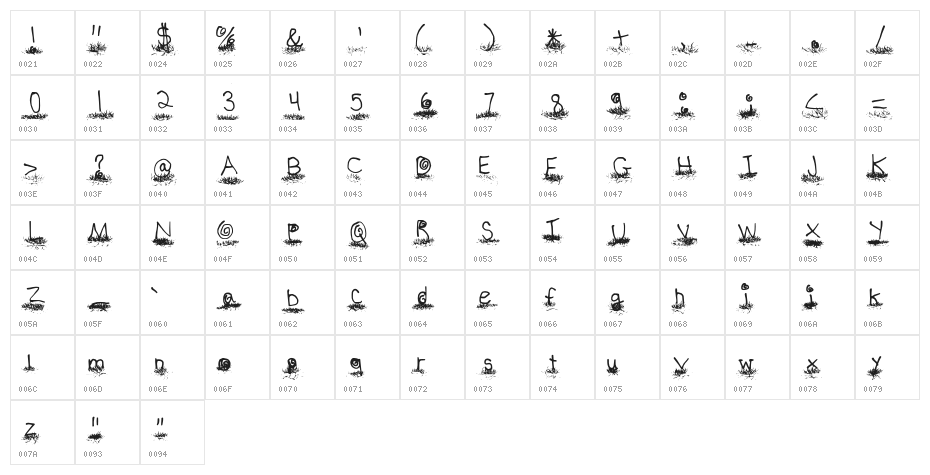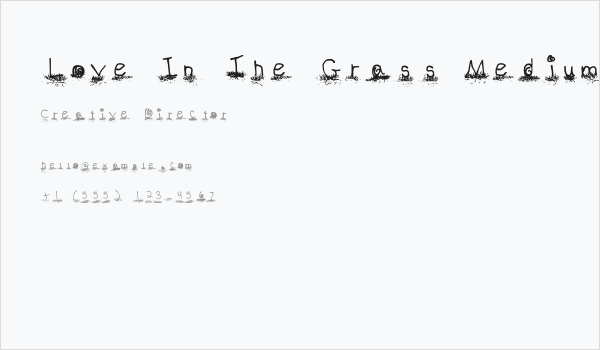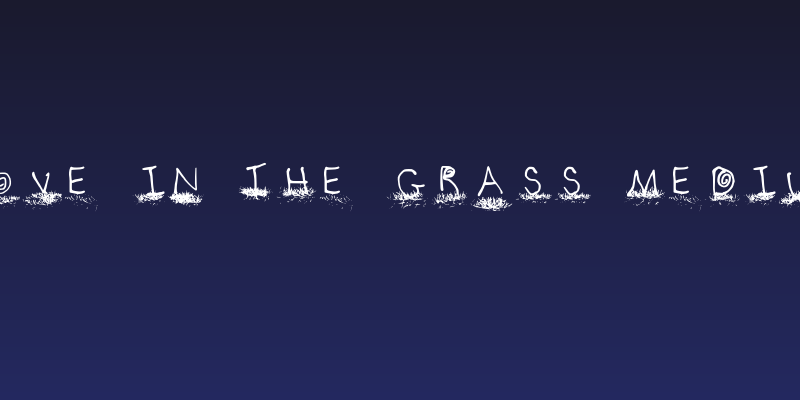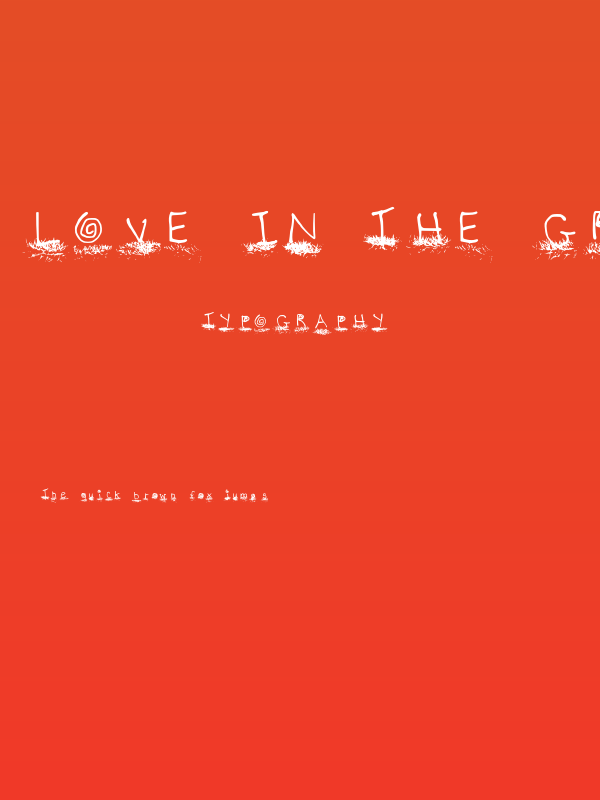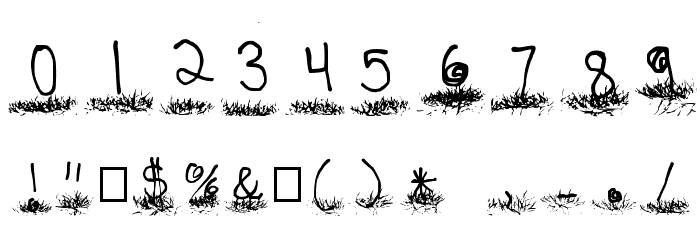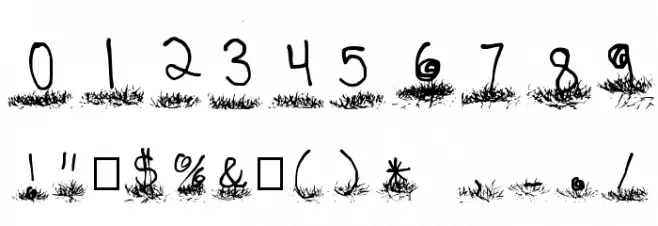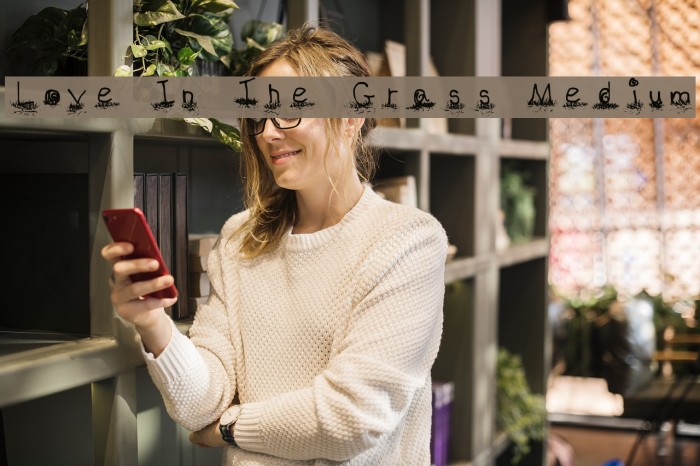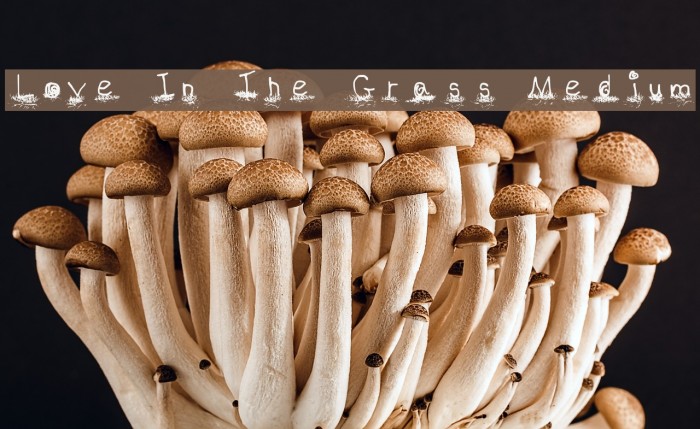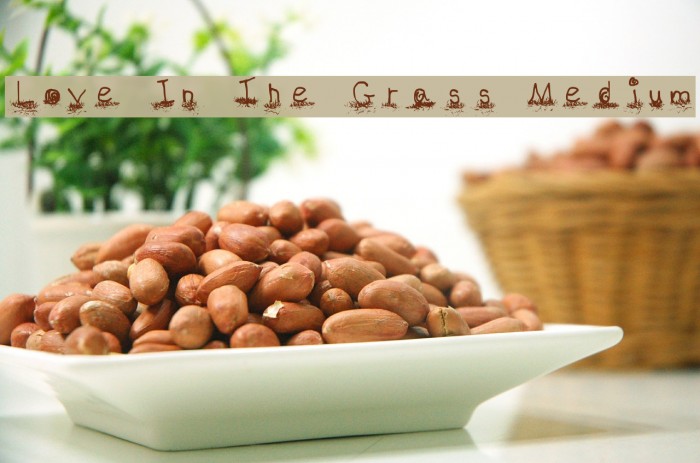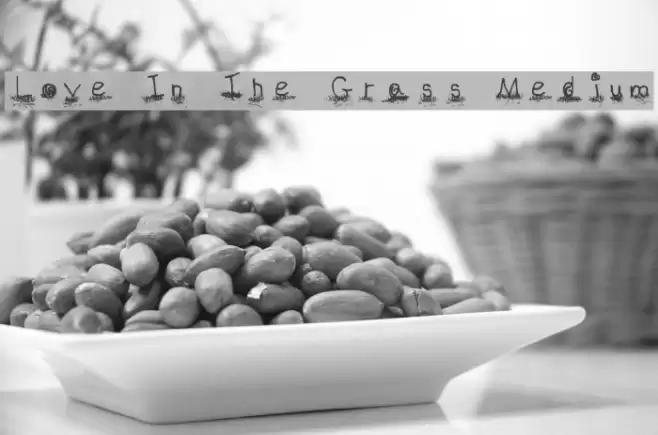
Love In The Grass Medium Font
| Область применения | Logos, Headlines, Invitations |
| Рекомендуемые проекты | Ideal for nature-themed invitations, children's book covers, eco-friendly brand logos, and playful greeting cards. |